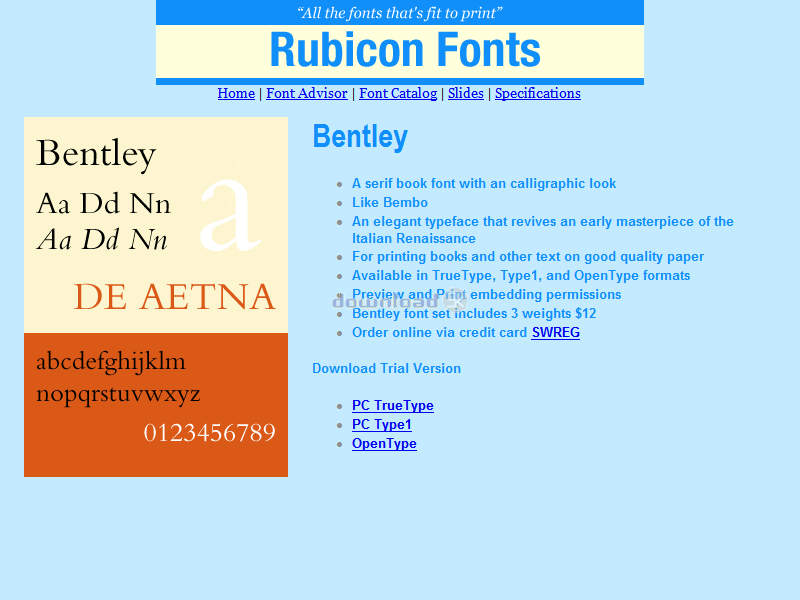
"Serif book font, calligraphic feel."
Une police serif livre avec un regard calligraphique. Comme Bembo. Pour limpression de livres et dautres textes sur du papier de bonne qualité. Une police de caractères élégante qui ravive un chef-dœuvre au début de la Renaissance italienne. Recommandé taille 12 points. Précis et laissé entendre, ce qui correspond mesures de police, jeu de caractères standard, crénage paires. Qualité dimpression professionnelle pour jet dencre, laser, typographe à 3500 dpi. Les acheteurs reçoivent 3 variantes de police comme suit: romain, italique, gras.Exigences: Older versions of Windows require Adobe Type Manager.